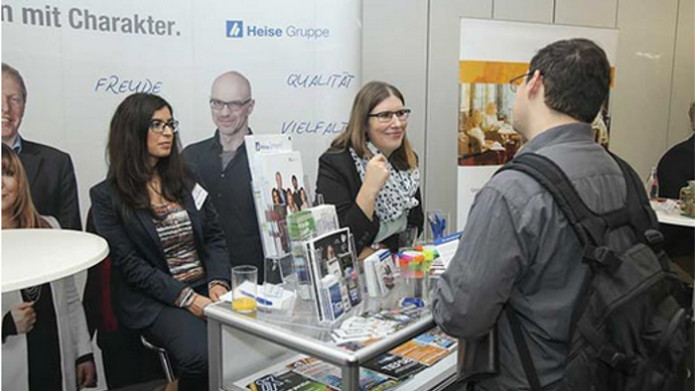
Handschrift auf Werbung für Heise MINT-Jobtag 2017
auf dem folgenden Bild (als Link auf Heise) als Werbung für den Heise MIT-Jobtag 2017 sieht man die Worte Freude, Qualität und Vielfalt in einer (Alltags-) Handschrift. Möglicherweise ist diese Schrift eine Blockschrift, also AllCaps? Ich konnte die Schrift in meinen Unterlagen nicht finden. Es gibt allerdings sehr viele ähnliche Schriften.
Auf die Schnelle habe ich auch keine PDFs von Heise gefunden, aus denen ich die Schriftinformationen auslesen könnte. Wer kennt diese Schrift zufälligerweise? Ich glaube mich erinnern zu können, dass ich diese schon mal in Werbung für eine Apotheken-Kette gesehen habe, da war die Schrift aber aufrecht. Möglicherweise wurde die Schrift auch schräggestellt?
Biro Script, gibt’s bei dafont.
In der Arbeitgeber-Broschüre wird sie verwendet:
Ich hab nach "heise freude qualität vielfalt" gegoogelt, drittes Ergebnis :-)